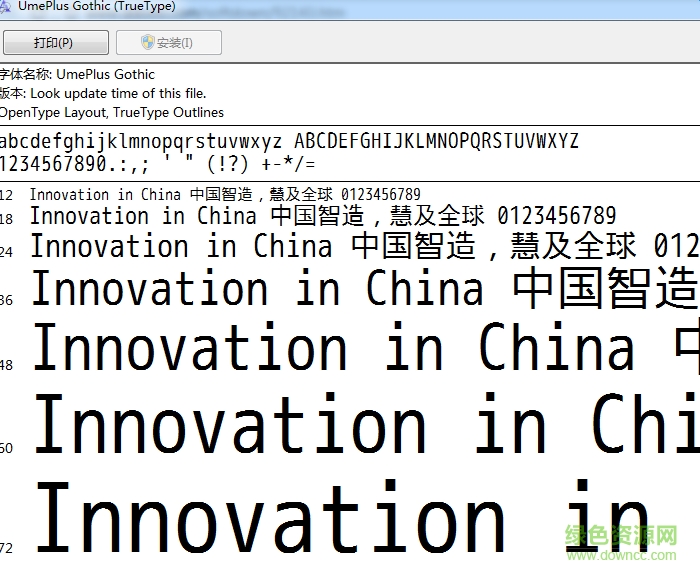
umeplus gothic字體是一款常見(jiàn)于游戲中的字體,一般是日本制作的游戲會(huì)常用到,也被稱為日本中文字體,如果您在運(yùn)行游戲的時(shí)候提示umeplus gothic缺少就是這個(gè)字體的缺少,安裝這個(gè)字體就可以了,有需要的朋友可以免費(fèi)下載收藏。